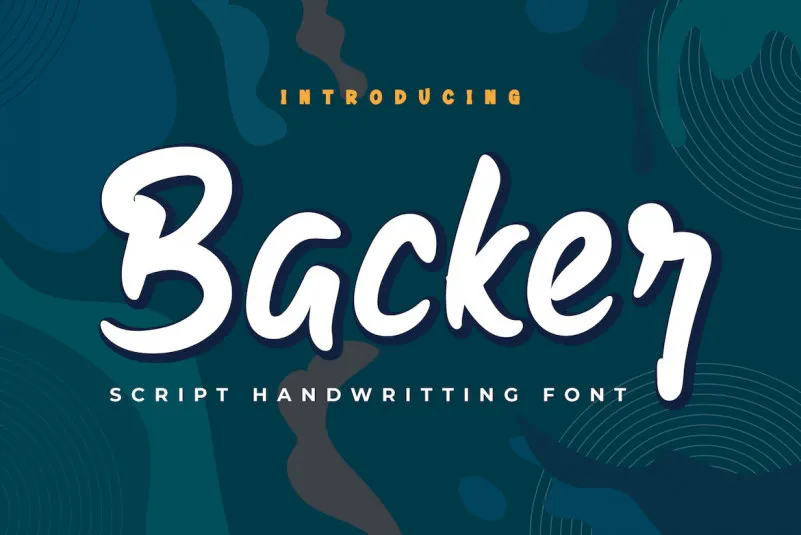
Backer Font – Fonte Grátis
Backer Font
A fonte Backer é ideal para projetos especiais que exigem uma combinação única de elegância e delicadeza. Criada com o toque suave e encantador de mão, essa font está especialmente adaptada para textos e cabeçalhos em trabalhos de design especializados. Suas linhas leves mas belamente arredondadas permitem que você crie uma fidelidade visual impressionante sem deixar transparecer a dificuldade na sua criação. Seja para um site, ou material gráfico para redes sociais, essa font oferece a sofisticação e o charme necessários para destacar seu design. Backer é perfeito para aqueles que buscam manter uma conexão suave entre o texto e as imagens sem deixar de lado a delicadeza do design tipográfico.
Designer: productype